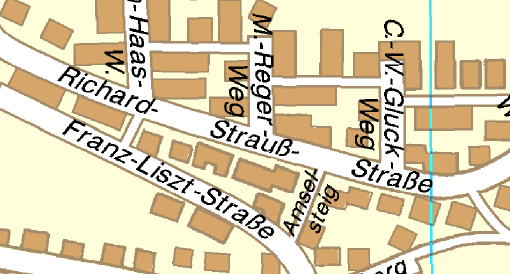
Neue Rechtschreibung?
Wie gehe ich denn mit einer Richard-Strauß-Straße um, die lt. amtlichem Straßenverzeichnis so heißt, der gute Mann aber doch mit ss statt ß geschrieben wird?
Wenn man danach googelt findet man für die falsche Schreibung mit ß keine Belege. Da scheint das Wissen der Leute die Konvention in die richtige Richtung gedrückt zu haben. Wikipedia, Google Maps etc. – überall mit Doppel-S.
Dem würde ich mich dann auch anschließen.
Wenn man danach googelt findet man für die falsche Schreibung mit ß keine Belege.…
Ja, zum Glück. Nur gibt mir der Eichstätter Stadtplan jenes aus:
Und es geht leider um genau jene Adresse …
Achso, okay. Ja, die wird wohl so geschrieben:
Ich bin immer an anderen Adressen im München rausgekommen.
Dann musst du das in diesem Fall beibehalten. Richard Strauss (wenn überhaupt die Straße nach jenem namhaften benannt ist) wurde im 19. Jahrhundert sicherlich auch gelegentlich mit ß geschrieben. Damals war das ja noch nicht so klar. Wenn die Straße dann von Anfang an so hieß, dann ist das als Eigenname auch nicht antastbar.
ok, dann nehm ich schon mal Anlauf, um über meinen Schatten zu springen … ;-)
Wenn du meine Schriftwahl anzweifelst, werfe ich den Ball gern zurück:
Bitte nenne mir die deiner Meinung nach am besten lesbare Frakturschrift in der deiner Meinung nach besten Digitalisierung. Lass mir ein PDF mit den Buchstaben in Kurven zukommen und ich werde noch einmal mit einer typischen Antiqua vergleichen, welche Schrift die meisten Leserlichkeitsstolperfallen aufweist.
Hier findest Du ein PDF mit den Buchstaben der Euler-Fraktur. Ich behaupte nicht, daß das die am besten lesbare Frakturschrift ist, aber es ist eine Schrift, deren Buchstabenformen sich gut unterscheiden — und darum scheint es Dir ja hauptsächlich zu gehen.
Du präsentierst hier mit dem Beispiel reiſen/reifen/reisen freimütig ein Paradebeispiel, …
Ich habe nicht vor, etwas zu verschweigen, oder die Wahrheit sonstwie zu verbiegen; laß uns die Karten offen auf den Tisch legen.
… das zeigt, dass typische Fraktursatzmerkmale eben gerade nicht auf optimale Leserlichkeit ausgelegt sind. Und das ist nur ein Beispiel von vielen.
Mich erstaunt, daß das eines von vielen Beispielen sein soll, denn ich habe lange überlegen müssen, bis es mir eingefallen ist. Wenn Dir noch mehr Minimalpaare zu f und ſ einfallen, laß es mich bitte wissen.
Wer auch sich auch nur ein bisschen mit der Physiologie des Lesens beschäftigt, weiß ja, dass wir nur ganz wenige Buchstaben scharf verarbeiten (Fovea). Der größte Teil wird beim flüssigen Fließtext-Lesen nur unscharf verarbeitet oder ganz übersprungen. Auch die oben von Joshua gezeigten »Positiv-Beispiele« zeigen nur eine äußerst schwache Unterscheidung von f und ſ.
Da müsste man beim Lesen jeweils jedes f und ſ einzeln fixieren, um es wirklich unmissverständlich lesen zu wollen.
In der Praxis passiert das natürlich nicht. Man liest im Zusammenhang und weiß so bei gängigen Wörtern ohnehin, welcher der beiden Buchstaben überhaupt in Frage kommt. Auf gut Deutsch: man rät, ob es ein f oder ſ ist. […] Es geht in der Regel völlig problemlos. Kommt aber ein Eigenname oder ein mir nicht geläufiges Wort, wird f/ſ sofort zur Stolperfalle.
Du scheinst zu übersehen, daß das runde s bei Wahrnehmung im peripheren Sichtfeld mit anderen Mittellängenbuchstaben wie a oder e zu verwechseln ist — und ich bezweifele sehr stark, daß es sich in den meisten (Antiqua-)Schriften von diesen Buchstaben bei unscharfer Wahrnehmung erheblich besser unterscheidet als das ſ vom f. Mit anderen Worten: das runde s dürfte in ähnlichem Umfang erraten und aus dem Zusammenhang erschlossen werden wie das lange ſ; und bei nicht geläufigen Wörtern muß man hier genauso innehalten und eigens fixieren.
Das ist nicht tragisch, aber wenn diese kleine Schwäche des Fraktursatzes dann auch noch rumgedreht wird, und man behauptet, dass das ſ ja ein Zeichen der Überlegenheit und besseren Leserlichkeit der Fraktur im Vergleich zur Antiqua ist, dann kann ich mich dem aus den oben genannten Gründen einfach nicht anschließen.
Ich leugne nicht, daß die Verwechselbarkeit mit dem f ein Nachteil des ſ ist. Das ſ hat jedoch nicht nur diesen Nachteil, sondern auch einige Vorteile; Argumente für und gegen diesen Buchstaben habe ich vor einiger Zeit in diesem Gespräch bereits aufgezählt. So lange es dazu keine ordentliche Studie gibt (und womöglich wird es nie eine geben), bleibt uns nichts anderes übrig, als für uns zu entscheiden, ob wir glauben, daß die Vor- oder die Nachteile des ſ (und auch sonst der Fraktur) überwiegen. Ich glaube, daß die Vorteile des ſ schwerer wiegen als seine Verwechselbarkeit mit dem f. Du kannst gerne etwas anderes glauben; es bleibt jedoch Dein Glaube und ist keine sachliche Beschreibung der Wirklichkeit.
Es ist schade, dass solche Diskussionen so unmöglich scheinen. Wir streiten hier über jede typografische Feinheit, aber sobald es irgendwie den Fraktursatz berührt, wittern die Fraktursatzfreunde gleich »Blasphemie« bezüglich ihres »Glaubens« und verteidigen das »Gesamtwerk Fraktursatz« mit Händen und Füßen. Warum ist es nicht möglich Unzulänglichkeiten aufzuzeigen oder Konventionsänderungen zu diskutieren und gegebenenfalls auch zu akzeptieren?
Schwache Leistung? Das ist jetzt eine plumpe unsachliche Behauptung, wenn sie mit solchen Argumenten kommt. Du hast dich (nehme ich an) noch nie mit Leserlichkeitsstudien beschäftigt, aber kannst dennoch sagen, dass diese hier schwach und voller Fehler ist? Und das dann mit solchen tollen Begründungen wie mangelnder Rechtschreibung oder fehlendem Sehstärketest (ohne erklären zu könne, warum das in diesem Fall von Belang wäre).
Sorry, jetzt exerzierst du genau die Dinge, die du mir hier vorwirfst und scheinst mich auch noch übertreffen zu wollen …